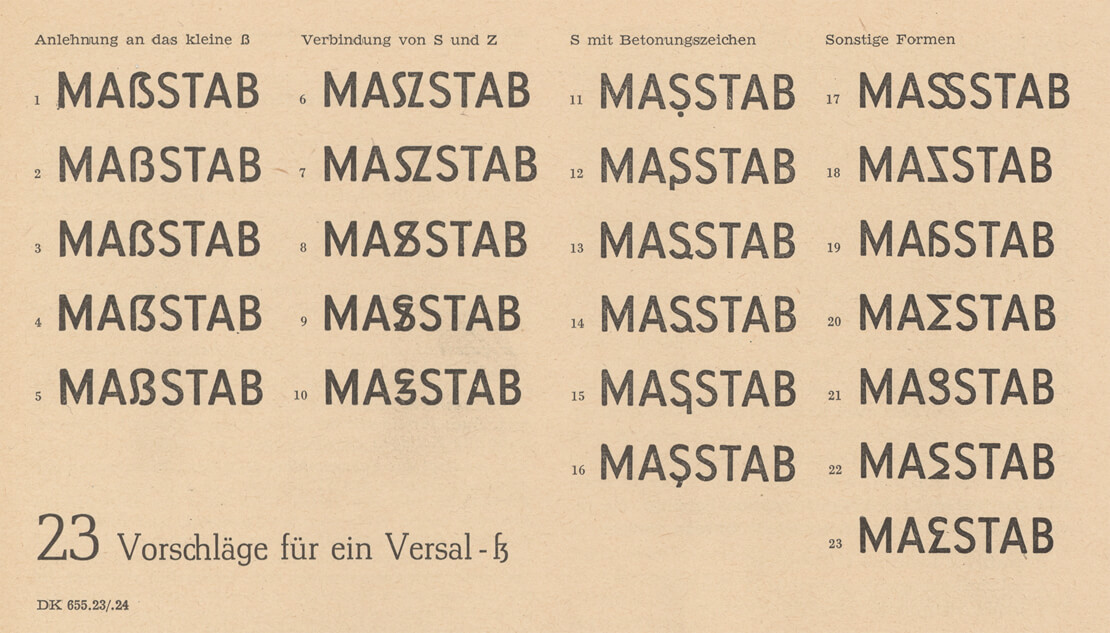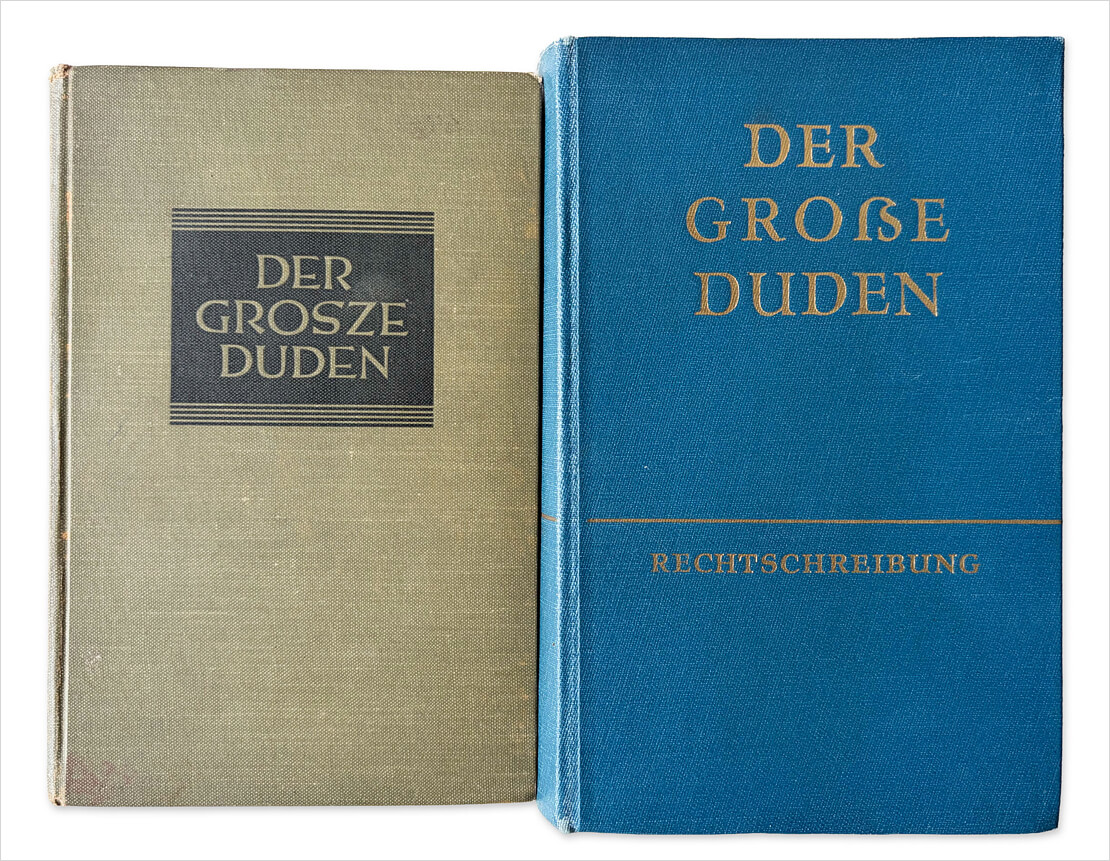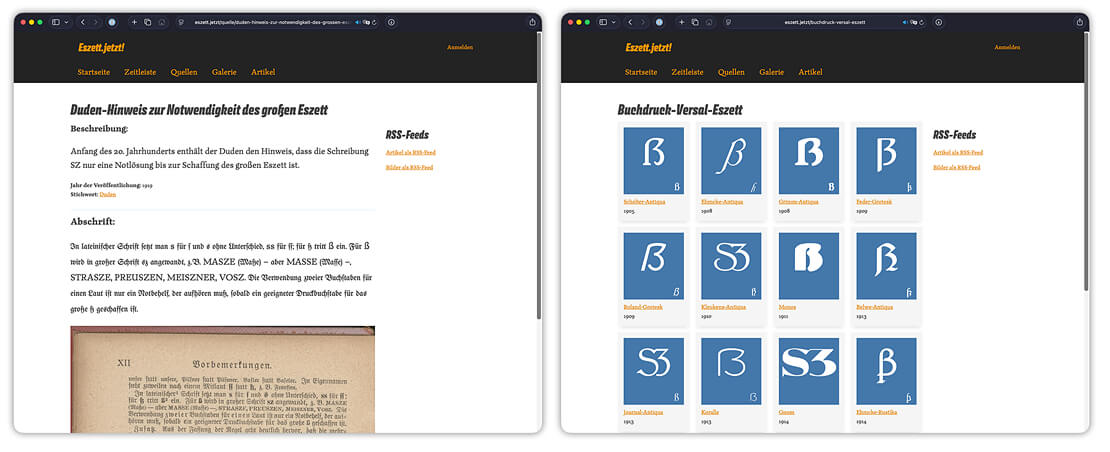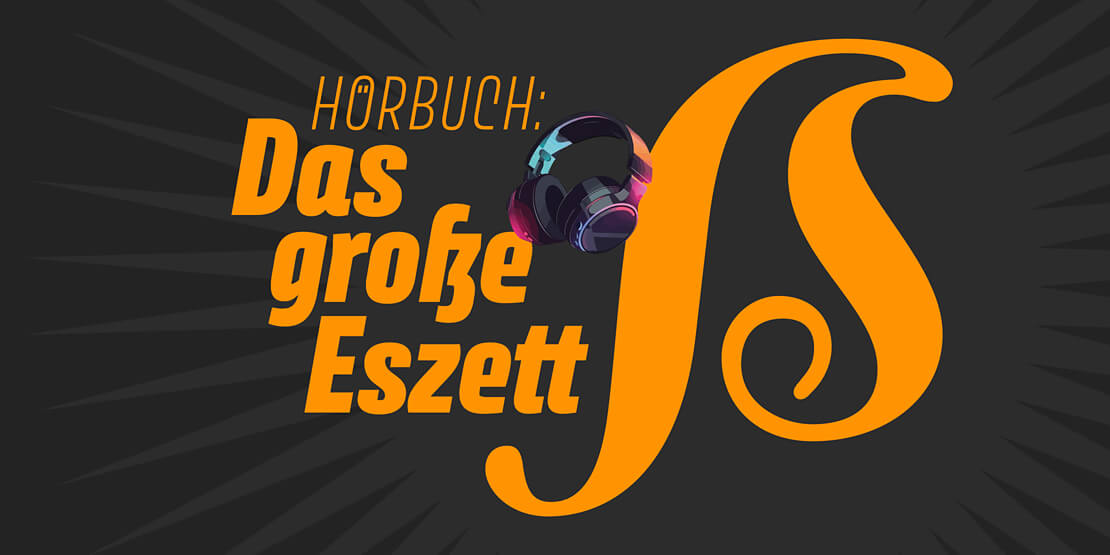
Das große Eszett: Typografie-Hörbuch sucht Unterstützung
Der Weimarer Typograf Ralf Herrmann plant ein mehrstündiges Hörbuch über die wechselvolle Geschichte des Eszett-Buchstabens. Das Projekt soll zudem den Aufbau eines frei zugänglichen Online-Archivs finanzieren. Die Kampagne läuft aktuell auf Kickstarter.
Obwohl das große Eszett bereits seit 2017 offizieller Bestandteil der amtlichen deutschen Rechtschreibung ist, ranken sich weiterhin viele Missverständnisse um das Zeichen. Das geplante Hörbuch von Ralf Herrmann greift diese Thematik auf und beleuchtet die historischen und funktionalen Zusammenhänge des Buchstabens in nie dagewesenem Detailreichtum.
Vom unfertigen Außenseiter zum amtlichen Zeichen
Der Buchstabe »ß« existierte über Jahrhunderte hinweg ausschließlich als Kleinbuchstabe und ursprünglich nur im Fraktursatz. Die Geschichte des Zeichens ist geprägt von ständigen Debatten: Mehrfach stand die komplette Abschaffung des Eszetts im Raum, gleichzeitig gab es seit dem 19. Jahrhundert immer wieder Bestrebungen, das Alphabet durch eine Großbuchstaben-Variante zu vervollständigen.
DDR-Entwürfe zum Versal-Eszett aus dem Jahr 1956 (© Abb.: Schriftkontor Ralf Herrmann)
Das Hörbuch soll sich nach einem Grundlagenkapitel ausführlich den drei historischen Anläufen zur Einführung des großen Eszetts widmen: u.a. den Debatten um 1900, den Diskussionen im grafischen Gewerbe der DDR Mitte des 20. Jahrhunderts sowie den finalen Schritten im 21. Jahrhundert. Dabei wird auch das komplexe Zusammenspiel zwischen Rechtschreibvertretern, Schriftgestaltern und Anwendern beleuchtet, das für die Einführung neuer Zeichen erforderlich ist. Zudem möchte die Publikation praxisnahe Informationen zur aktuellen Anwendung des Buchstabens liefern.
Der große Duden (© Abb.: Schriftkontor Ralf Herrmann)
Neues Recherche-Portal geplant
Parallel zum Hörbuch soll ein umfassendes Web-Portal entstehen. Geplant ist, dass dieses datenbankbasierte Archiv Quellen, historische Fachtexte, Schriftmuster und Entwürfe bündelt und dauerhaft kostenfrei zugänglich macht. Historische Texte mit abgelaufenem Urheberrecht werden außerdem dafür eigens transkribiert und mithilfe spezieller Webfonts digital aufbereitet.
Eszett-Webportal (© Abb.: Schriftkontor Ralf Herrmann)